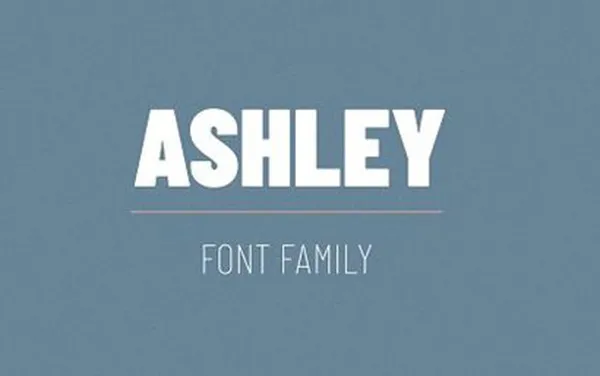
Ashley Font Family
A Ashley Font Family é uma elegante família de tipo all-caps sans serif projetada para dar um toque moderno a qualquer projeto. Esta família conta com 16 pesos do tipo, meticulosamente concebidos para um olhar impresso. Ashley não apenas oferece grande versatilidade sozinha, mas também se destaca como uma escolha perfeita quando usada em conjunto com logomarcas existentes e elementos de identidade corporativa. Esta família de fontes é ideal para aplicativos no campo da publicação, como capítulos e subtítulos em livros, manchetes em revistas e até mesmo para logotipos, embalagens ou design empresarial. Com a Ashley Font Family à sua disposição, você terá o tipo perfeito para dar vida aos seus projetos de design.